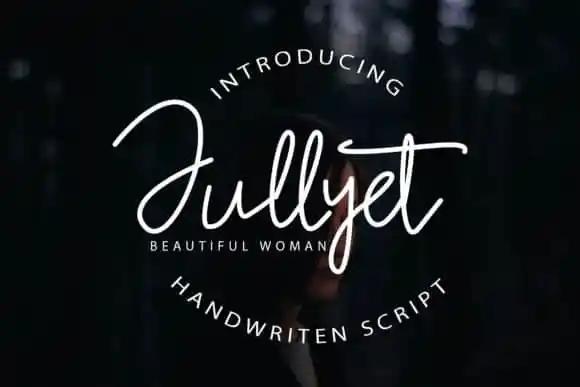
Jullyet Handwritten Font – Download Grátis
A Juliyet Handwritten Font é uma elegante tipografia frondosa cuidadosamente criada com uma pitada de romantismo. Ela surge do talentoso designer_handles Creative na 99designs. Esta tipografia suave se adapta perfeitamente a qualquer ideia de design, adicionando um toque lúdico e romântico a quaisquer projetos que você esteja criando. Seja para cartões personalizados ou editoriais gráficos mais sofisticados, Juliyet Handwritten oferece uma perspectiva única e vibrante em seu universo de fontes script, tornando-a um excelente recurso para designers visuais atentos ao detalhe.